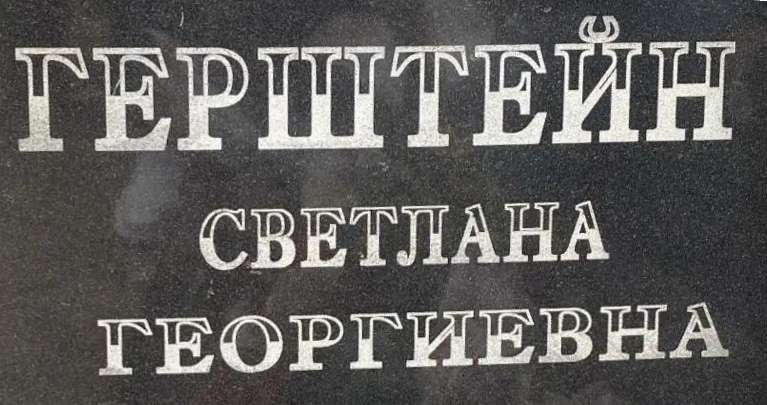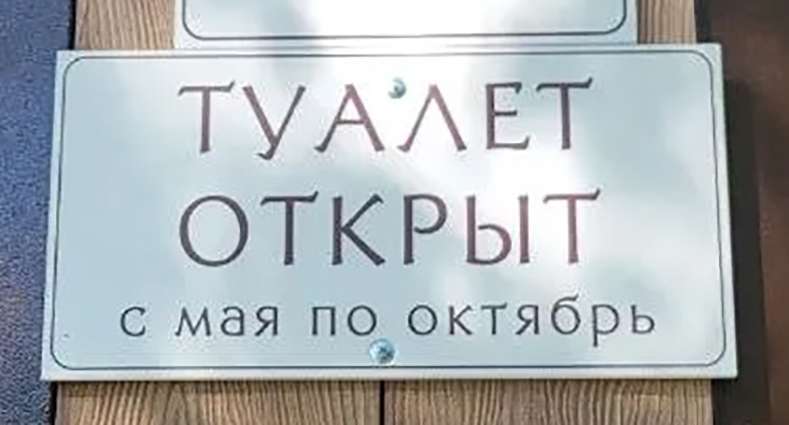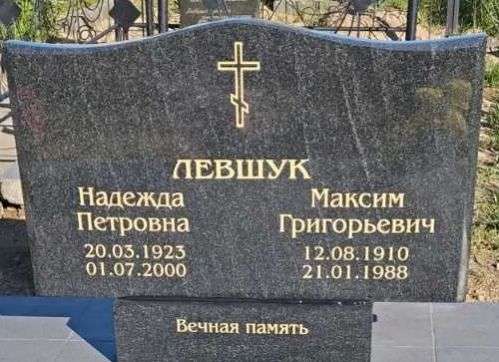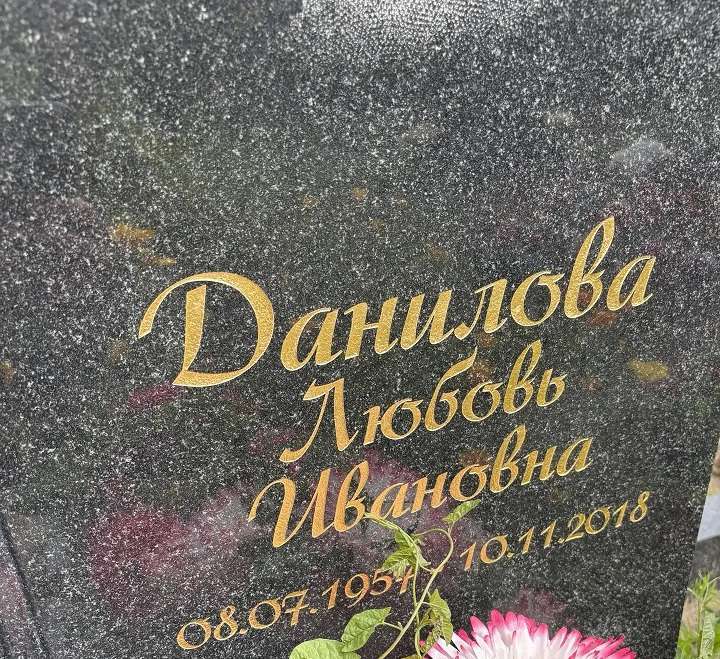
AID Опубликовано 26 июня Здравствуйте, помогите определить шрифт? Или это делалось с помощью какого ни будь плагина или строчки делили вручную?
Раю2020 Опубликовано 4 июля Здравствуйте! Помогите пожалуйста распознать шрифт! Нигде не могу найти.
Romeo Опубликовано 10 июля Коллеги,напомните пжста что за шрифт..что то оч знакомое,но у меня нету такого Сам нашел. Если что название ArconaC 1
Romeo Опубликовано 13 августа Коллеги, доброго времени суток. Подскажите, что за шрифт, не могу найти. Похож на Academy ,но по букве М и Л не бьется. Спасибо
fenix Опубликовано 14 августа (изменено) Коллеги форумчане!!! Помогите пожалуйста найти шрифт название Изменено 14 августа пользователем fenix
"Девчонка" Опубликовано 15 августа @perez Похож на Majestic или PopularScript 1
Romeo Опубликовано 15 августа В 13.08.2026 в 16:58, Romeo сказал: Коллеги, доброго времени суток. Подскажите, что за шрифт, не могу найти. Похож на Academy ,но по букве М и Л не бьется. Спасибо Коллеги все еще прошу помощи